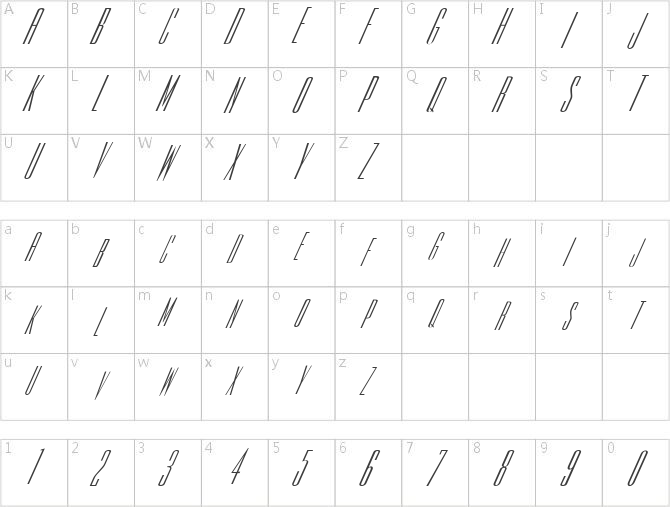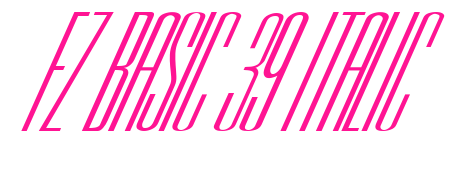
FZ BASIC 39 ITALIC
FZ BASIC 39 ITALIC介紹
FZ BASIC 39 ITALIC字體字庫是一款讓人賞心悅目、百看不厭的英文字體,適合各類廣告和產品包裝設計應用,字體大小0.03MB,格式為ttf字體,上傳用戶是ㄚòひ慬偶鰢,作者/版權方為未知
FZ BASIC 39 ITALIC效果圖